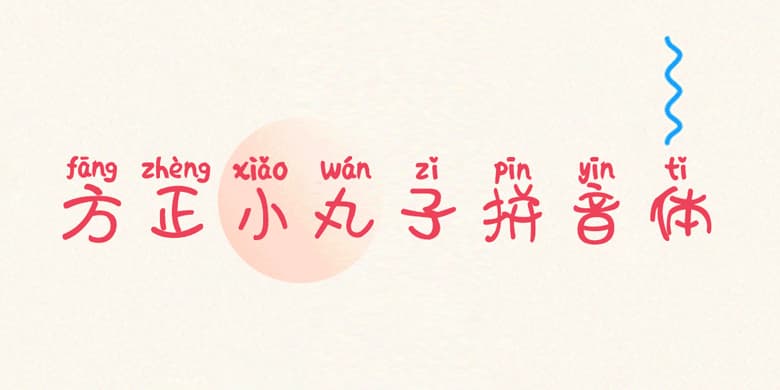
方正手迹-小丸子拼音体
品牌:方正手迹设计师:龚永辉发行时间:2020字库编码:大陆简体(GB2312-80)分类:创意书写字体属性:精品字
方正手迹-小丸子拼音体
这是个充满童趣的字体,线条简单,字形可爱。全部采用曲线的行笔风格,似鱼眼,有的部件打破常规,透着年幼的单纯稚气,让人觉得轻松又可爱,相当充满个性。适用于少年儿童类的书刊、品牌广告和产品包装设计,以及社交网络的个性化用字。